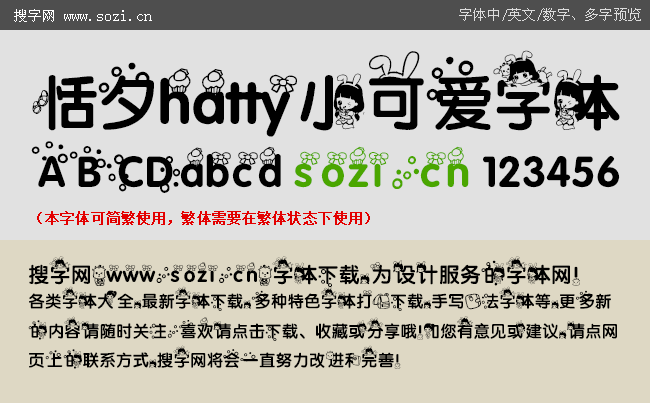
hatty小可愛字體
搜字網(wǎng)給大家提供一款很有趣的手機(jī)中文字體下載。修改者給他起名為hatty小可愛字體,這款手機(jī)字體是在粗圓體字體筆畫間插入了大量的可愛卡通圖案。在具備粗圓字體醒目清晰端正的風(fēng)格同時,卡通味也特別濃,是一款非常可愛的卡通字體,特別適合喜歡手機(jī)字體個性一些的朋友在手機(jī)上安裝使用。